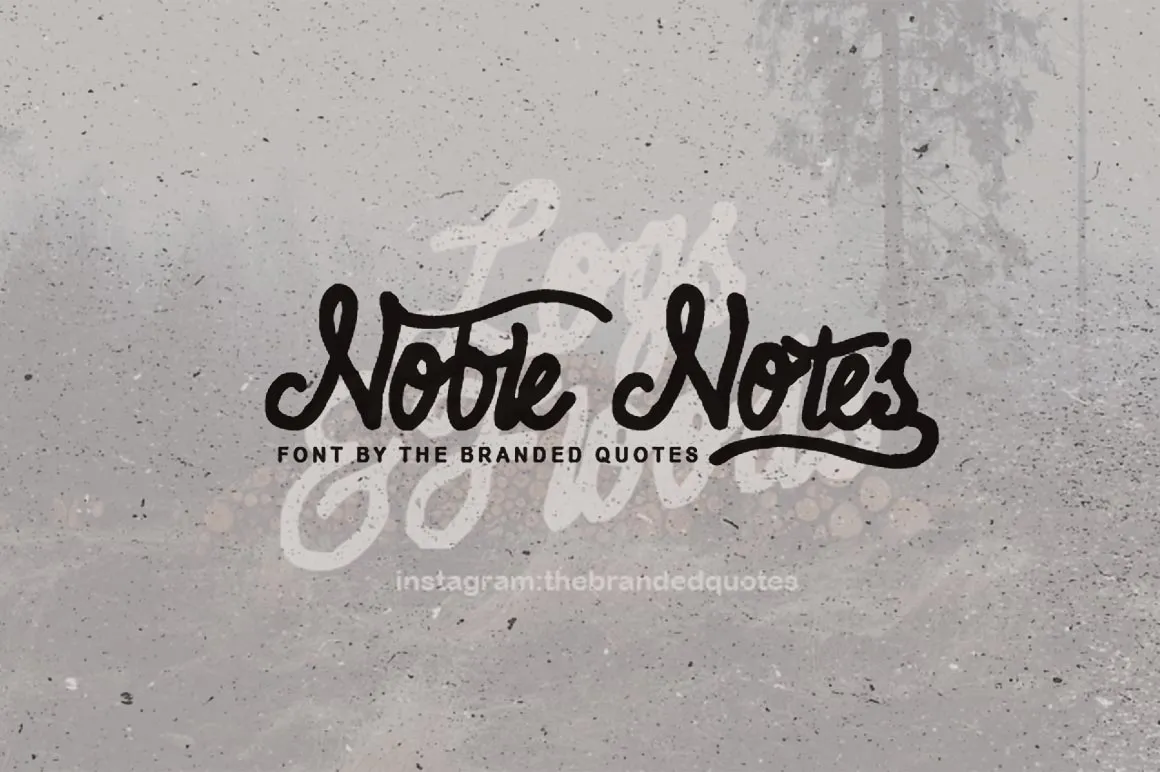
Noble Notes é uma linda fonte display criada pelo designer Hamilton, ideal para aqueles que buscam um toque sofisticado e elegante em seus projetos digitais. Essa fonte é perfeita para ambientes de negócios formais ou para criações artísticas mais refinadas, oferecendo uma mistura atraente de força e delicadeza. Com seu design minimalista mas elegante, Noble Notes transmite confiança sem perder sua sofisticação. A fonte inclui ilustrações gratuitas e um texto em alta resolução para aqueles que desejam adicionar mais detalhes e textura a seus projetos. Para obter acesso aos elementos adicionais mencionados na descrição original, basta enviar uma mensagem de email para . Esta fonte é perfeita para quem busca um design único e sofisticado que reflete seu trabalho de maneira elegante e profissional.